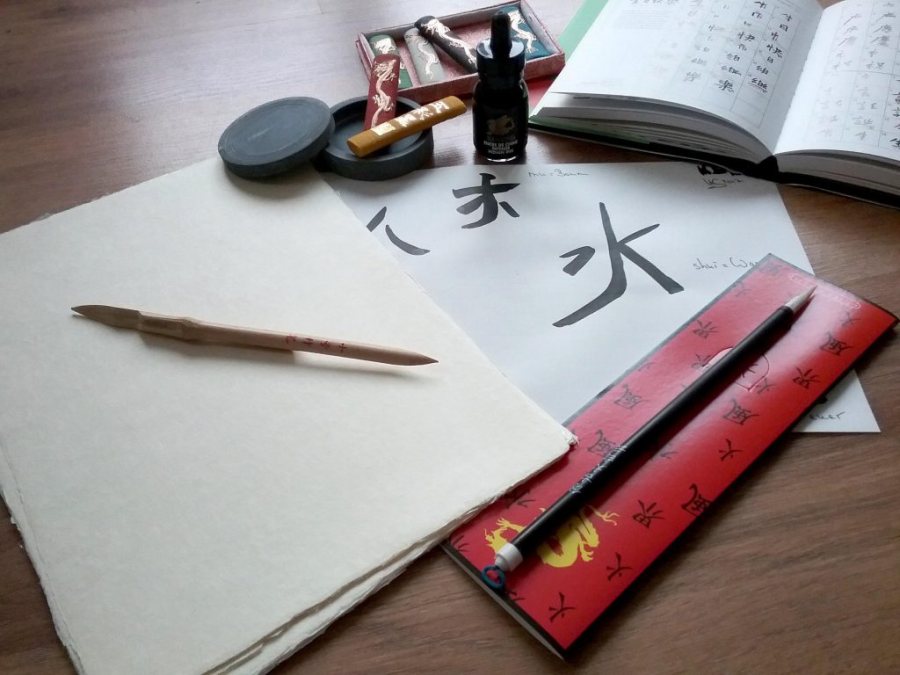
Die Kunst der Chinesischen Kalligrafie
Sie können es schon der Überschrift entnehmen, die Chinesische Kalligrafie ist weit mehr, als eine Ansammlung von Schriftzeichen. Sie ist eine erhabene Kunst, die sich über viele Jahrtausende hinweg immer wieder verändert hat. Nie aber an Schönheit, Ästhetik und Stolz verloren, sondern im Gegenteil, hinzugewonnen hat.
Uns allen ist sie geläufig, jedoch ist den meisten nur wenig über ihre Entwicklung bekannt. Für alle, die ein wenig mehr über dieses wundersame, anmutende Kunstform erfahren möchten, habe ich ein wenig recherchiert und im Folgenden zusammengetragen. Begeben Sie sich nun mit mir auf eine kleine Entdeckungstour, ins Reich der asiatischen Schriftkunst. Die chinesische Kalligrafie ist das älteste noch gebräuchlichste Schriftsystem der Welt. Forscher konnten die Schriftzeichen bis zur Shang-Dynastie 1600 v.Chr. zurückverfolgen. So fand man in Banpo/China Inschriften, die Ähnlichkeiten mit den späteren Schriftzeichen aufwiesen. Sie sollen der Ursprung der chinesischen Schriftzeichen sein.
Im Laufe der Entwicklungsgeschichte formten sich verschiedene Schriftformen. Im Einzelnen unterscheidet man zwischen der Knochenschrift – Jia Gu Wen – ca. 1600 v. Chr. Diese Schrift stammt aus der Shang-Dynastie. Sie wurde für das Legen von Orakeln genutzt. Hierfür wurden Zeichen in Schildkrötenpanzer oder Tierknochen geschnitzt und diese mit pflanzlichen Pigmenten bestäubt. Dann erhitzte man die Knochen. Dabei entstanden Risse und die Pigmente lösten sich auf. So entstanden neue Risse und Farbverläufe, die vom Zeremonienmeister gedeutet werden konnten.
Große und kleine Siegelschrift – Dai Zhuan und Xiao Zhuan – ca. 1100 bis 200 v. Chr.
Die große Siegelschrift entwickelte sich aus der oben genannten Knochenschrift, für sie nutze man schon Bambusblätter als Schriftgut. Ein paar Jahrhunderte später, hatten sich diese Schriftzeichen derart etabliert, dass Philosophen wie Konfuzius sich ihrer bedienten, um ihre Gedanken und Überlegungen schriftlich festzuhalten. Um 200 v.Chr. verfeinerte der Minister Li Si die Siegelschrift, sodass die Zeichen nun regelrecht elegant und geschwungen anmuteten. So entstand die Kleine Siegelschrift. Dieser Schritt in der Entwicklung der Schriftzeichen war sehr bedeutend.
Kanzleischrift – Li Shu – ca. 200 v.Chr.
Eine Legende besagt, dass ein Gefängnisinsasse seine Zeit damit verbrachte, die damalige Schrift zu verändern. Sein Ziel war es, Dokumente schneller erstellen zu können. Er nahm der Kleinen Siegelschrift die runde Form und einige kleinere Striche hier und da. Die Zeichen waren nun kantiger und ließen deshalb schneller schreiben. Dennoch wiesen sie eine große Vielfalt auf.
Kursivschrift und/oder Grasschrift – Cao Shu – 48 v.Chr.
Diese Schrift wurde von einem Gelehrten der Han Dynastie erarbeitet. Er fügte den Zeichen wieder Rundungen hinzu und verband diese miteinander. So entstand die kursive Form der Kanzleischrift. Ihre Zeichen sind fließend und können schnell geschrieben werden. Da sie aus vielen miteinander verbundenen Strichen besteht, wird sie auch die Grasschrift genannt – sie erinnert an Halme. Da beim Schreiben – entgegen allen anderen Schriftformen der Chinesischen Kalligrafie – kaum abgesetzt werden muss, hat sie auch heute noch einen hohen künstlerischen Wert.
Regelschrift – (Wie) Kai Shu – ca. 220 n.Chr.
Die Regelschrift entwickelte sich aus der Kanzleischrift. Erstmals entdeckt wurde sie in der Wei-Zeit ca. 250 n.Chr.. Sie weist eine klare Linienführung auf und wirkt in ihrer Grundform regelrecht quadratisch. Bis heute ist sie in China sehr beliebt.
Schnellschrift – (Han) Xin Shu – ca. 220 n.Chr.
Ein Schreibstil, der irgendwo zwischen der Kursivschrift und der Regelschrift liegt. Er gehört zu den beliebtesten Stilen der Kalligrafen. Der berühmteste unter ihnen war der Kalligraf und Beamte Huang Xi Zhi, 317 – 365 n.Chr., der mehr als 1.000 Kalligrafien schuf. Seine Kunstwerke titulierte er mit den Worten: „Jeder waagerechte Strich ist ein Wolkenhaufen in Schlachtordnung. Jedes Häkchen ist ein Bogen von großer Spannkraft. Jeder Punkt ist ein Felsen, der vom Gipfel stürzt. Jede Ausbiegung ist ein trockenes Weingerank von hohem Alter. Jeder rasche, frei hingesetzte Strich ist ein Wettläufer am Start.“
So ist in China die Kalligrafie weit mehr als nur schön schreiben – sie ist eine angesehene Kunstform, „shu fa“ genannt, gleichgesetzt mit Malerei, Musik und Literatur. Sie ist sehr populär und schon die kleinen Kinder müssen sie erlernen. Und das nicht nur, weil es eine hochgeschätzten Kunstform ist. Laut dem Dictionary of Chinese Variant Form gibt es im Chinesischen mehr als 100.000 Schriftzeichen. Von diesen sollen der allgemeinen chinesischen Bevölkerung, aber nur rund 50.00 bekannt sein. Davon wiederum werden lediglich ca. 7.00 häufig gebraucht. Zudem bestehen die Chinesischen Schriftzeichen aus einem sinn- und einem lautgebenden Teil. So kann ein falsch gesetzter oder weggelassener Strich schon den Wortlaut komplett verändern.
Die chinesische Kalligrafie kann nicht mit dem doch recht starr anmutendem Schreiben der westlichen Kalligrafie verglichen werden. Sie ist vielmehr ein Zusammenspiel aus Malerei und Bewegungskunst. Jede noch so leichte Handbewegung wird vom Pinsel aufgenommen und spiegelt sich als Emotion im Schriftbild wieder. So bedarf es vor allem Konzentration, innere Ruhe und rhythmisches Feingefühl, um einerseits die Schriftzeichen korrekt und leserlich zu schreiben, sie andererseits aber auch harmonisch darzustellen. Denn auch die Ästhetik spielt in der chinesischen Kalligrafie eine große Rolle.
Schließen möchte ich mit einem Zitat von Picasso: „Wenn ich früher in China gelebt hätte, wäre ich anstatt eines Malers ein Kalligraf geworden „.